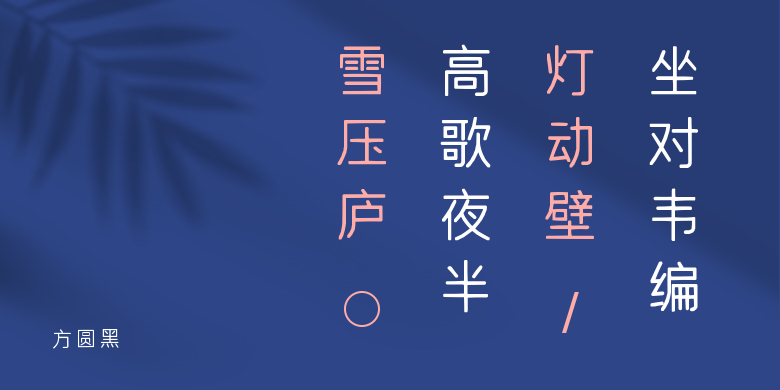
方圆黑
方圆黑,这款字体结构工整、笔画清晰,兼顾美观与易读性,适用于标题、正文、海报、包装、LOGO 等多种场景。字形优雅稳定,风格百搭耐看,适配日常排版与创意设计,让文字呈现更舒适、更具质感。方圆黑一笔一画,皆是细节,以均衡的比例、流畅的线条打造舒适视觉体验,字形端正大气,风格简约现代。无论是商业设计、品牌宣传还是日常排版,都能轻松驾驭,让文字更有格调与力量。方圆黑字体下载。